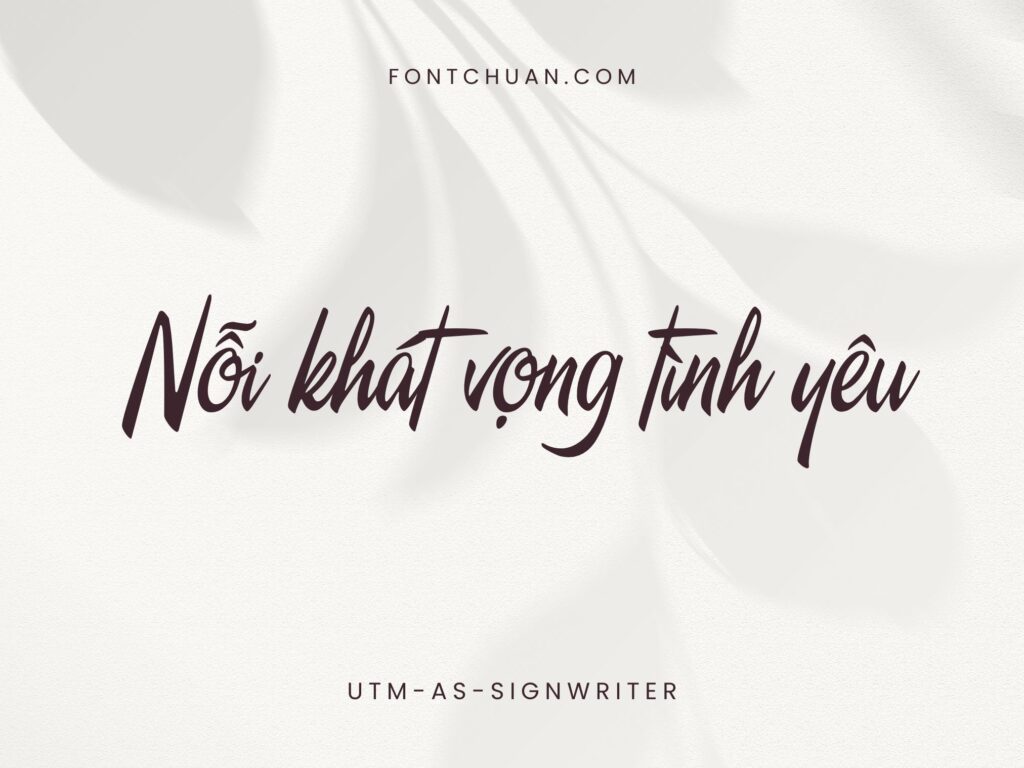
Font UTM A&S Signwriter Việt Hóa
UTM A&S Signwriter là phiên bản Việt hóa của kiểu chữ A&S Signwriter, một Font Script mang phong cách Font Handwritten viết tay tự nhiên và năng động. Font này được thiết kế với các đường nét mềm mại, uyển chuyển, gợi nhớ đến nghệ thuật viết biển hiệu truyền thống. Phiên bản Việt hóa do Đinh Kiên thực hiện, hỗ trợ đầy đủ tiếng Việt cùng hơn 100 ngôn ngữ khác. Đây là một trong những font được thành viên Font Chuẩn sưu tầm và chọn lọc nhằm phục vụ cộng đồng thiết kế trong các dự án cần sự sáng tạo và cá nhân hóa.
UTM A&S Signwriter có cấu trúc chữ nối liền mạch, các nét chữ được thiết kế với độ nghiêng vừa phải và độ dày đồng đều, tạo cảm giác thân thiện và dễ tiếp cận. Font này phù hợp cho các ứng dụng như thiết kế logo, tiêu đề, bao bì sản phẩm, thiệp mời và các ấn phẩm truyền thông khác. Những ngành nghề như quảng cáo, thiệp cưới, giáo dục và ẩm thực có thể tận dụng UTM A&S Signwriter để tạo điểm nhấn độc đáo và thu hút trong thiết kế.